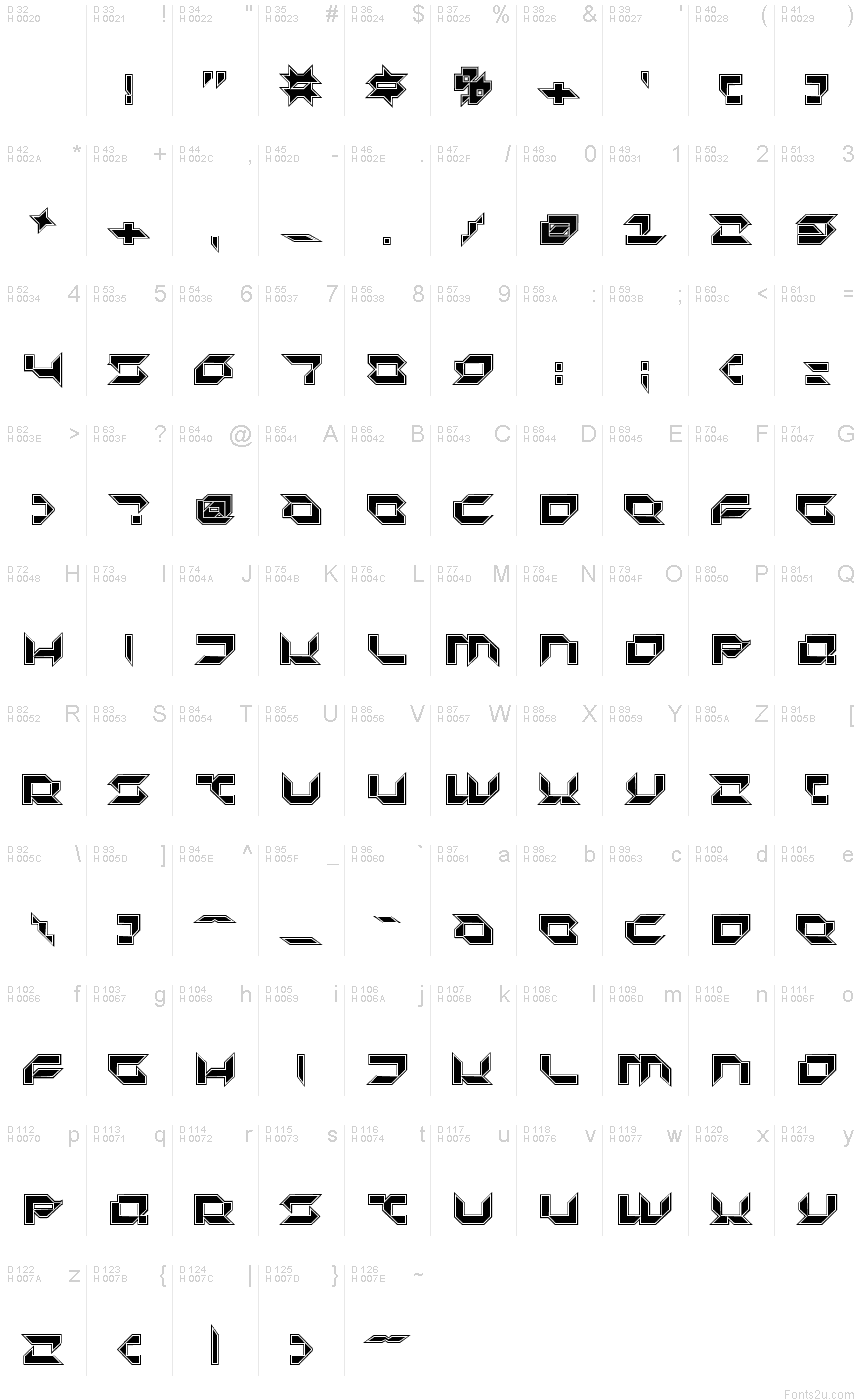
Pluranon Pro autorstwa Milana Zrnica i Tommy'ego Cary'ego to darmowy techniczny krój pisma typu display, pisany wielkimi literami, z ostrym, wczesnocyfrowym klimatem. Litery zbudowane są z ciężkich, czarnych bloków otoczonych podwójnym konturem, z przyciętymi rogami, ściętymi krawędziami i połączeniami w kształcie strzałek, dzięki czemu alfabet sprawia wrażenie maszynowego, a nie tylko geometrycznego.
Doskonale odnajduje się w plakatach science-fiction, logotypach gier, ulotkach klubowych, planszach tytułowych i okładkach albumów, gdzie warstwowe krawędzie nadają krótkim słowom mocny, futurystyczny wyraz. Jako darmowy font, sprawdza się również w monogramach i przyciągających wzrok nagłówkach, ponieważ wielkie litery posiadają własną obwódkę i głębię bez konieczności dodatkowego stylizowania.